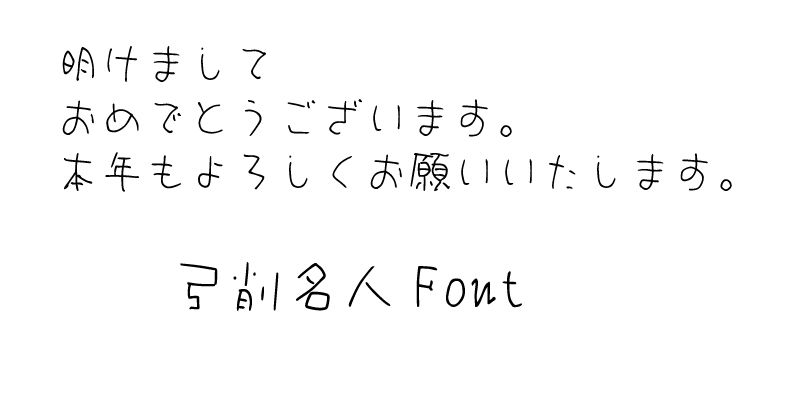
Diese Schriftenserie enthält handgeschriebene japanische Originalschriften, die auf Kalligrafie basieren und 2002 veröffentlicht wurden. Mit ihrem warmherzigen Aussehen lenken diese Schriften das Auge des Lesers auf die wichtigsten Punkte eines Designs.